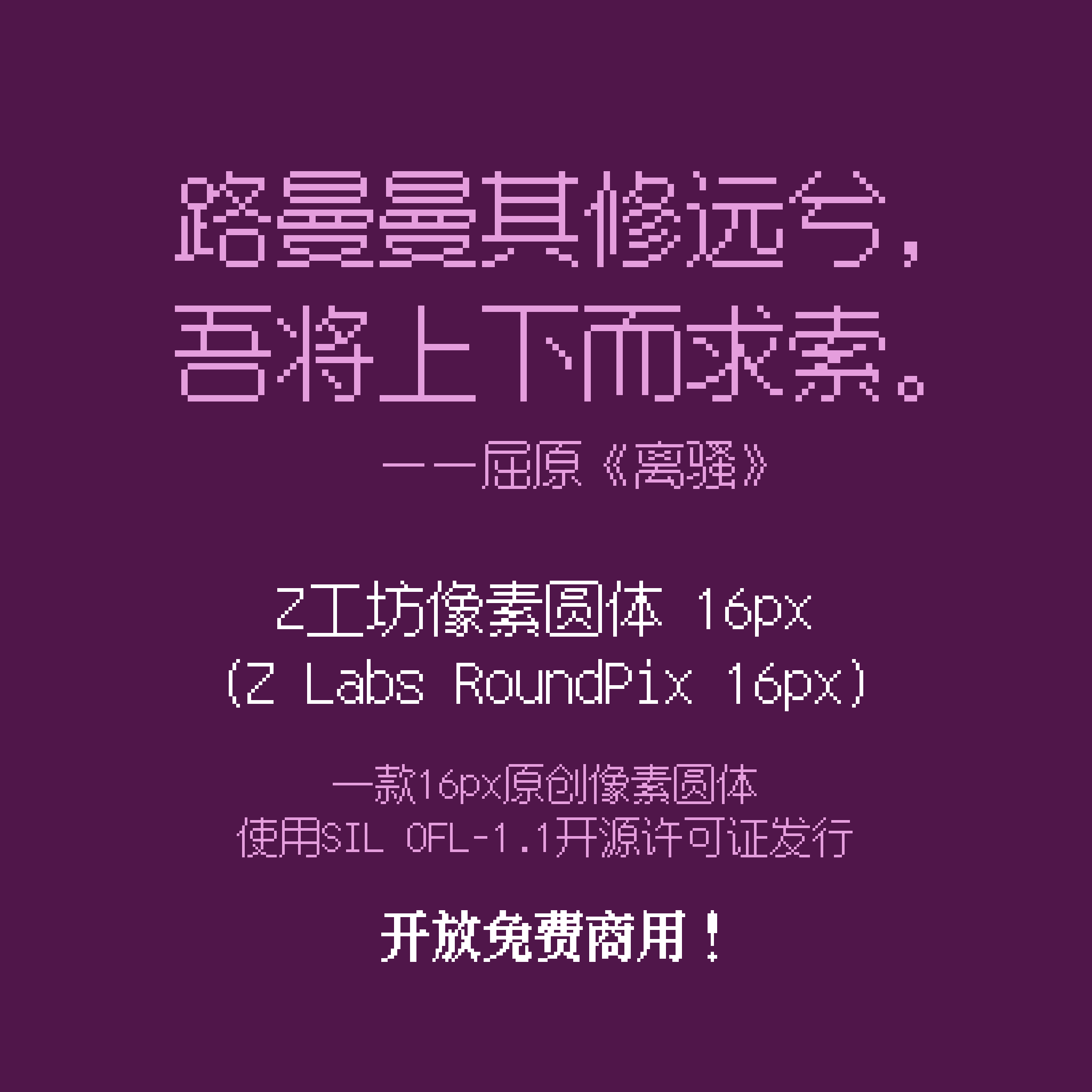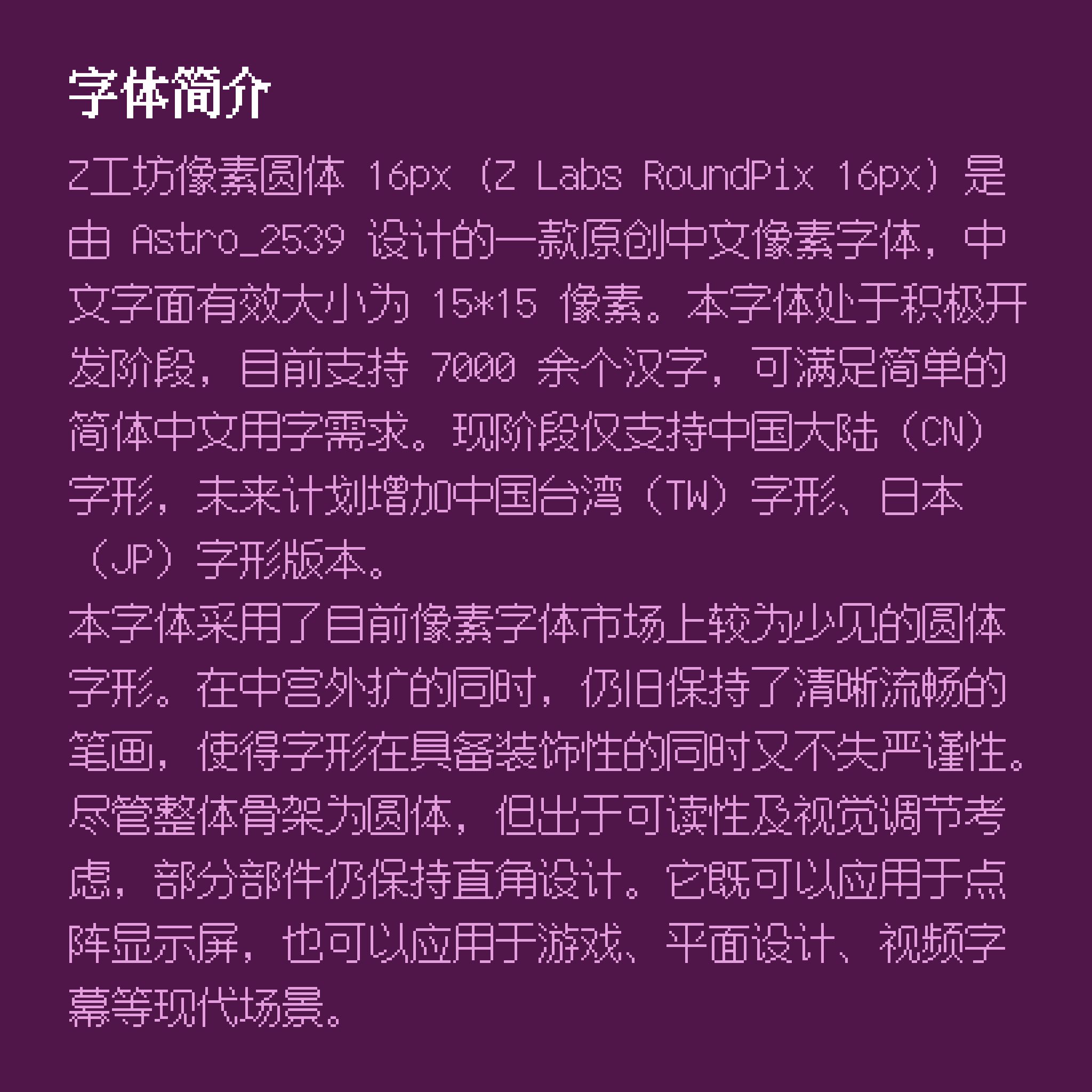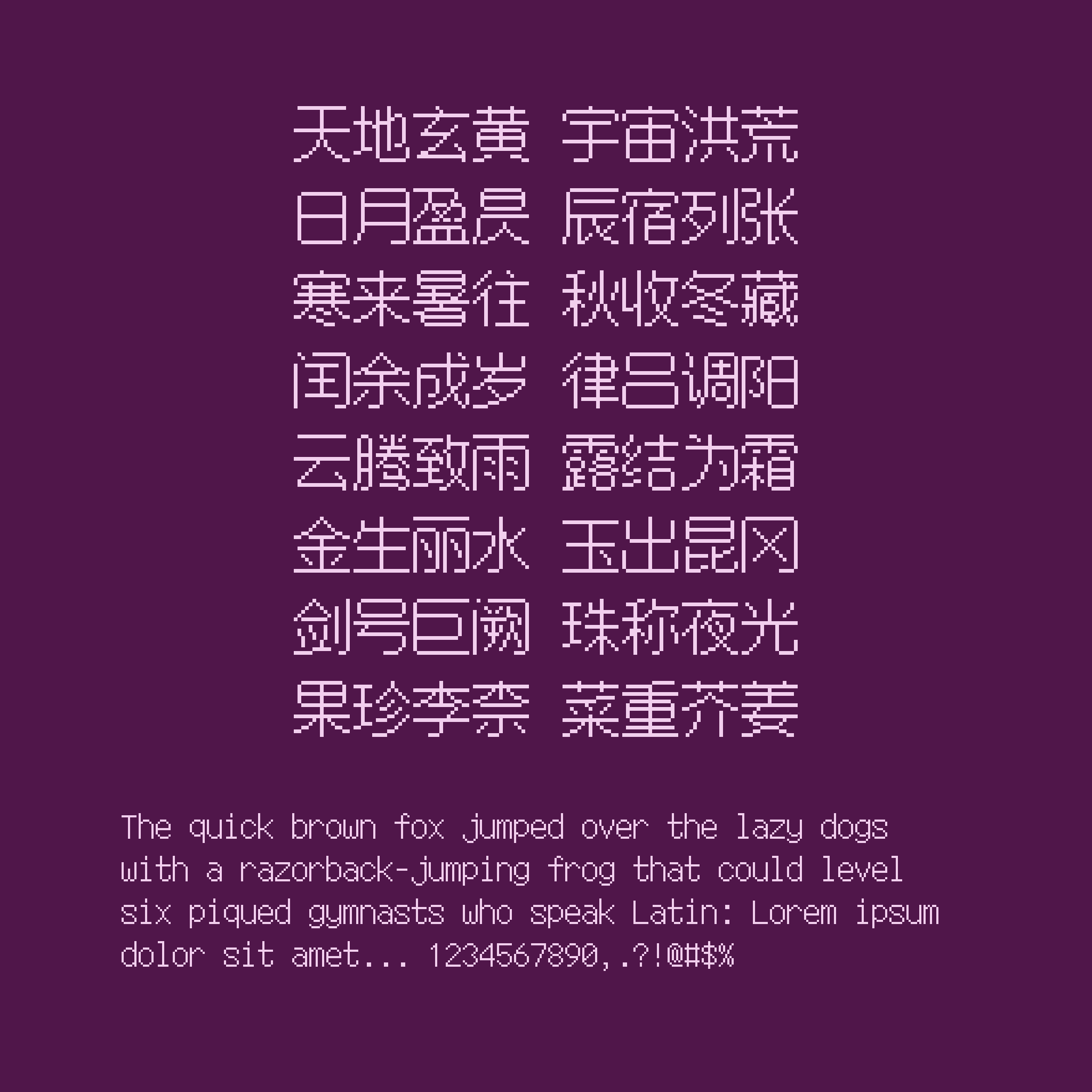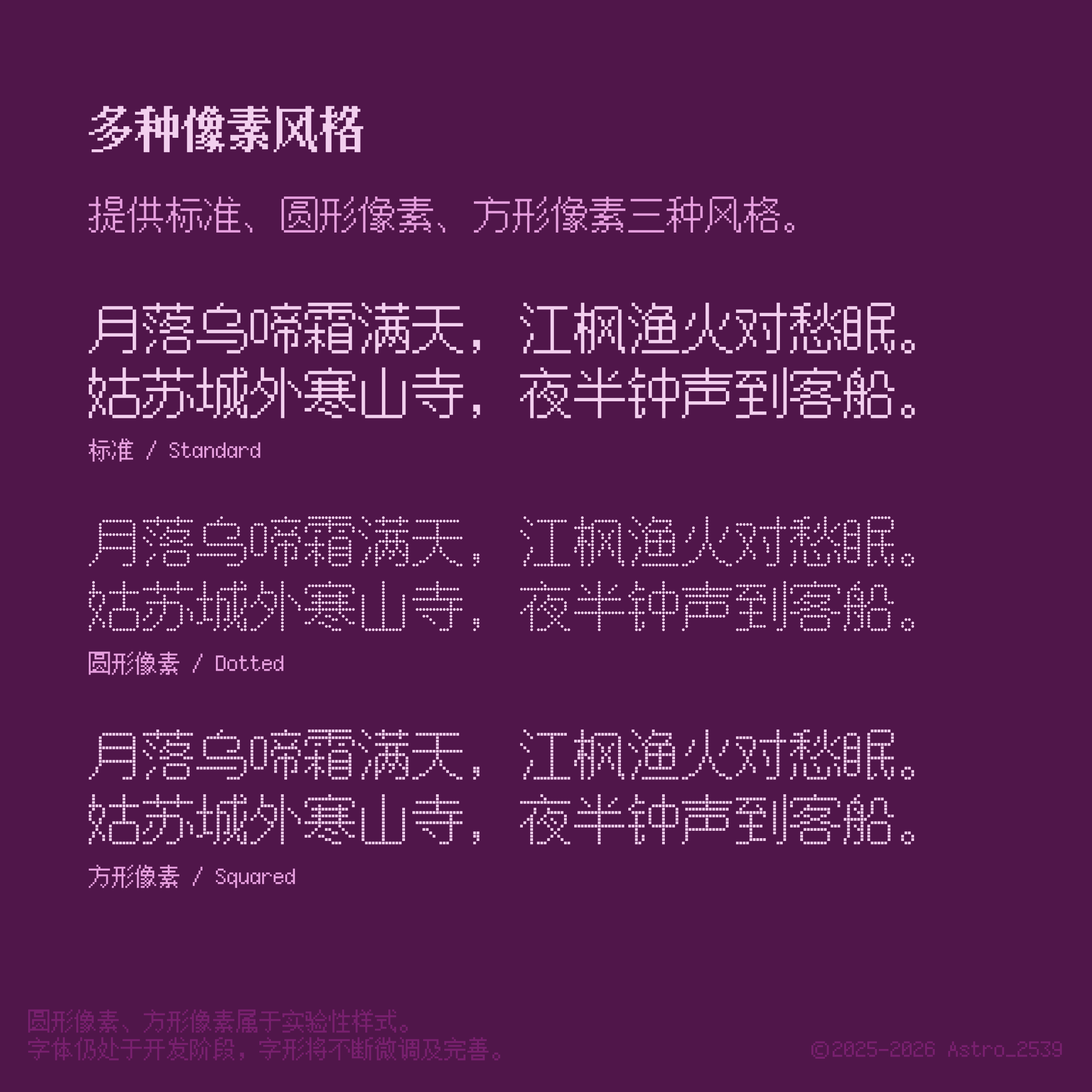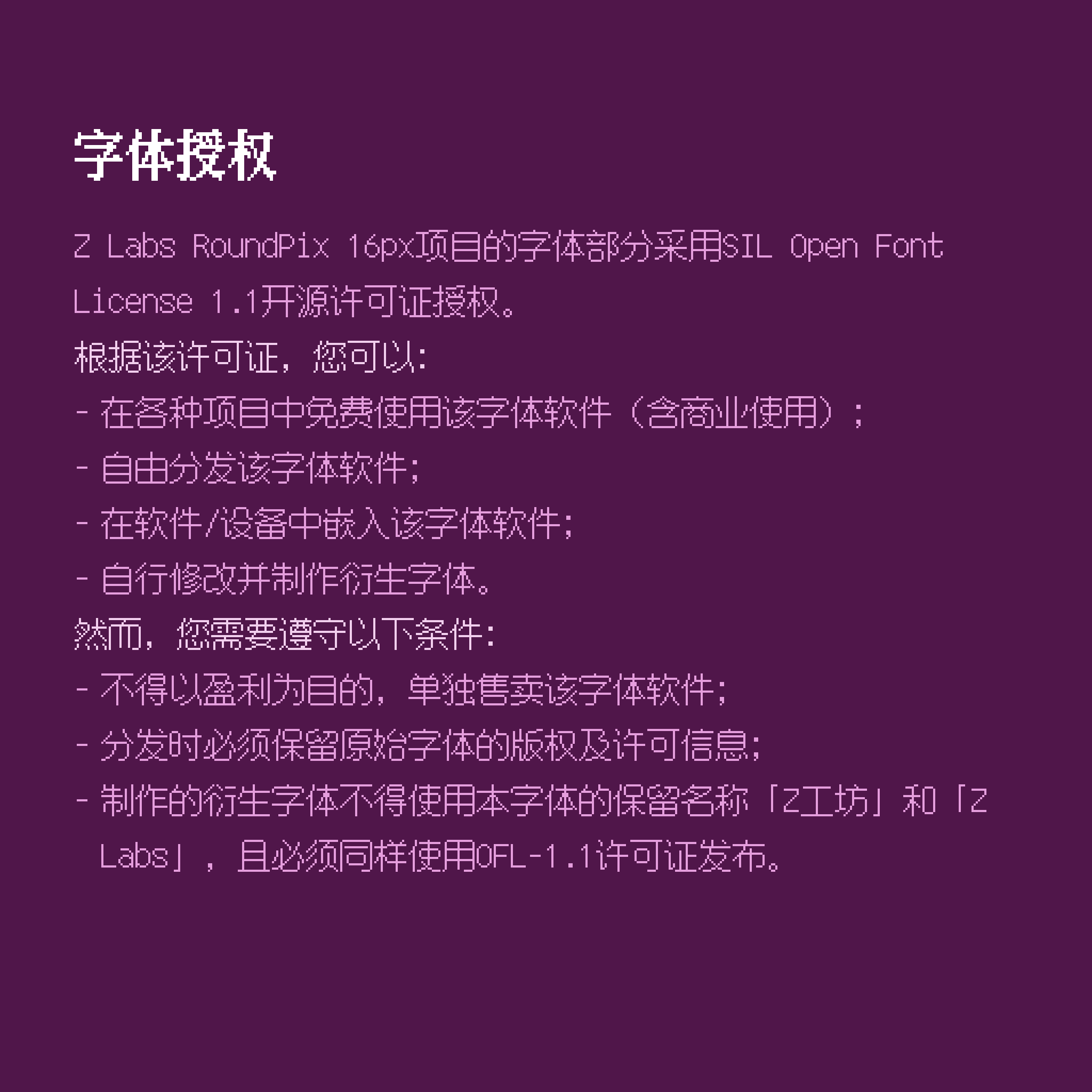
「Z Labs RoundPix 16px」(Z工坊像素圆体 16px) 是一款规格为 16px 的中文像素字体(汉字实际占用大小为 15*15),采用圆体字形风格,西文字符按等宽规格绘制。
本项目处于开发阶段,目前支持 GB/T 2312 所有汉字、常用西文及常用标点符号,可满足多数简体中文汉字使用需求。
此字体仍处于开发与调整阶段,目前存在中宫不均匀、汉字部件不一致等问题,敬请谅解。
字形变体
目前仅支持中国大陆(CN)字形变体。
注:日本(JP)字形变体已经开始制作,仓库已更新相关文件。
取形参考自「Zen Maru Gothic」,大致以JIS90为基准,而非采用较新的JIS2004标准。
汉字
中国大陆变体字形(CN)
✅ GB/T 2312 (6763 / 6763)
🚧 《通用规范汉字表》(6654 / 8105)
🚧 Big5 常用汉字表(3472 / 5401)
🚧《常用国字标准字体表》(3197 / 4808)
🚧 jf7000 当务字集基本包(3987 / 6373)
🚧 GB/T 12345(4822 / 6866)
🚧 JIS X 0208(3541 / 6355)
ℹ️ 共计支持汉字:7042